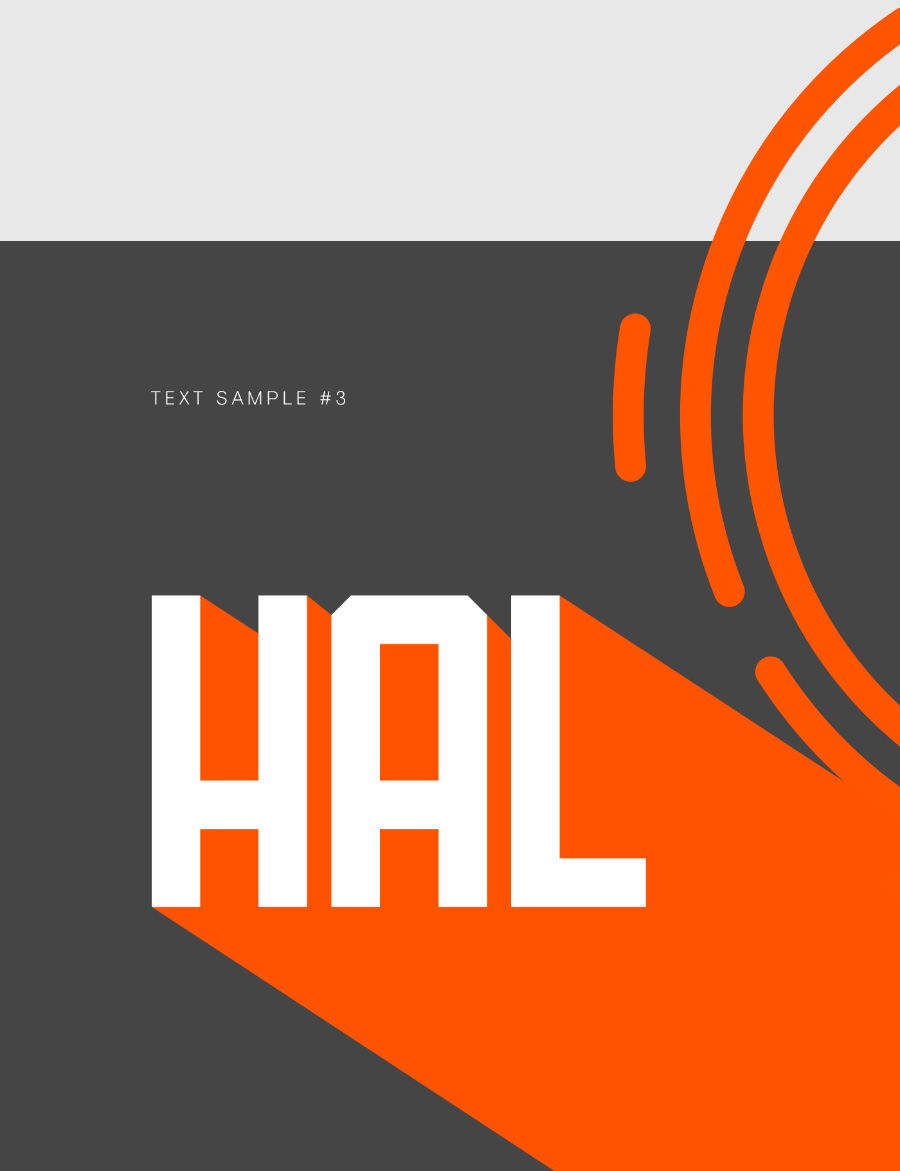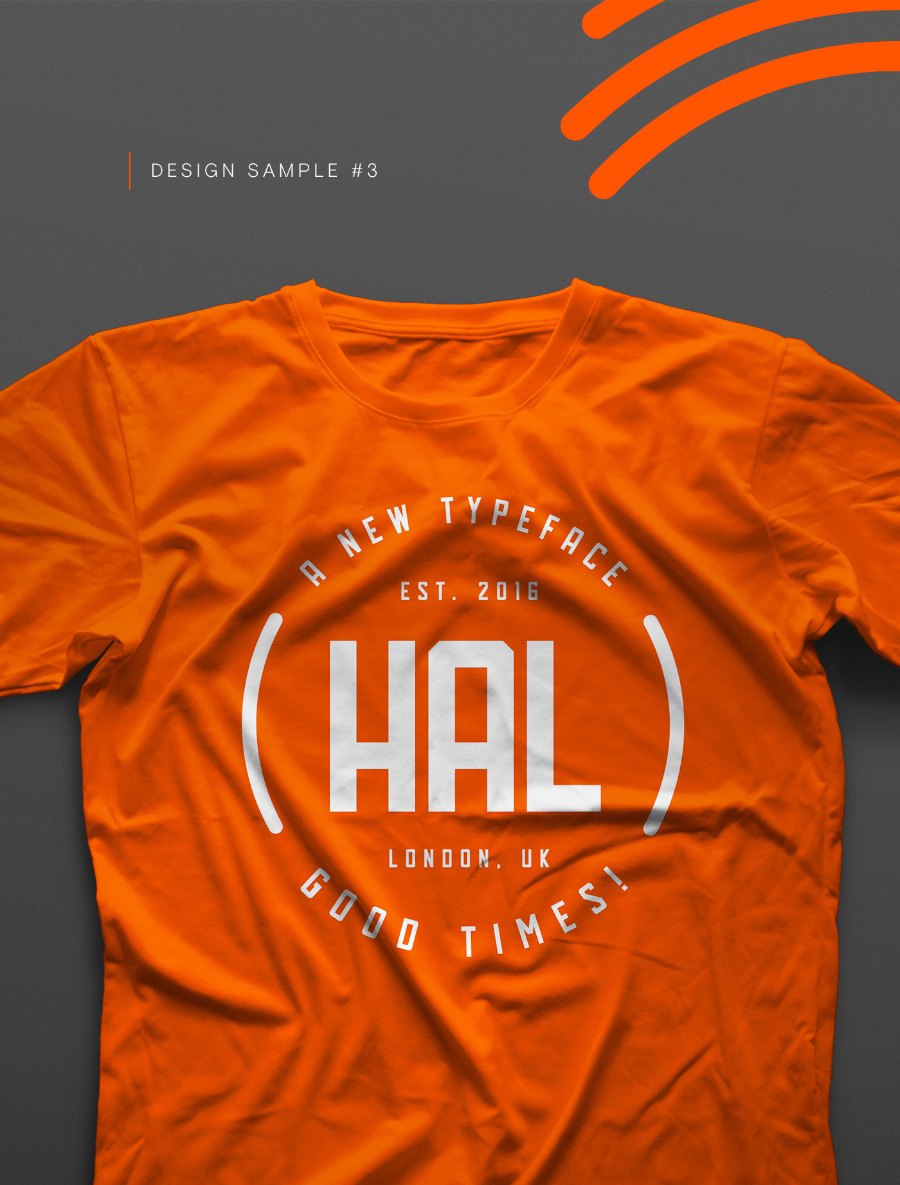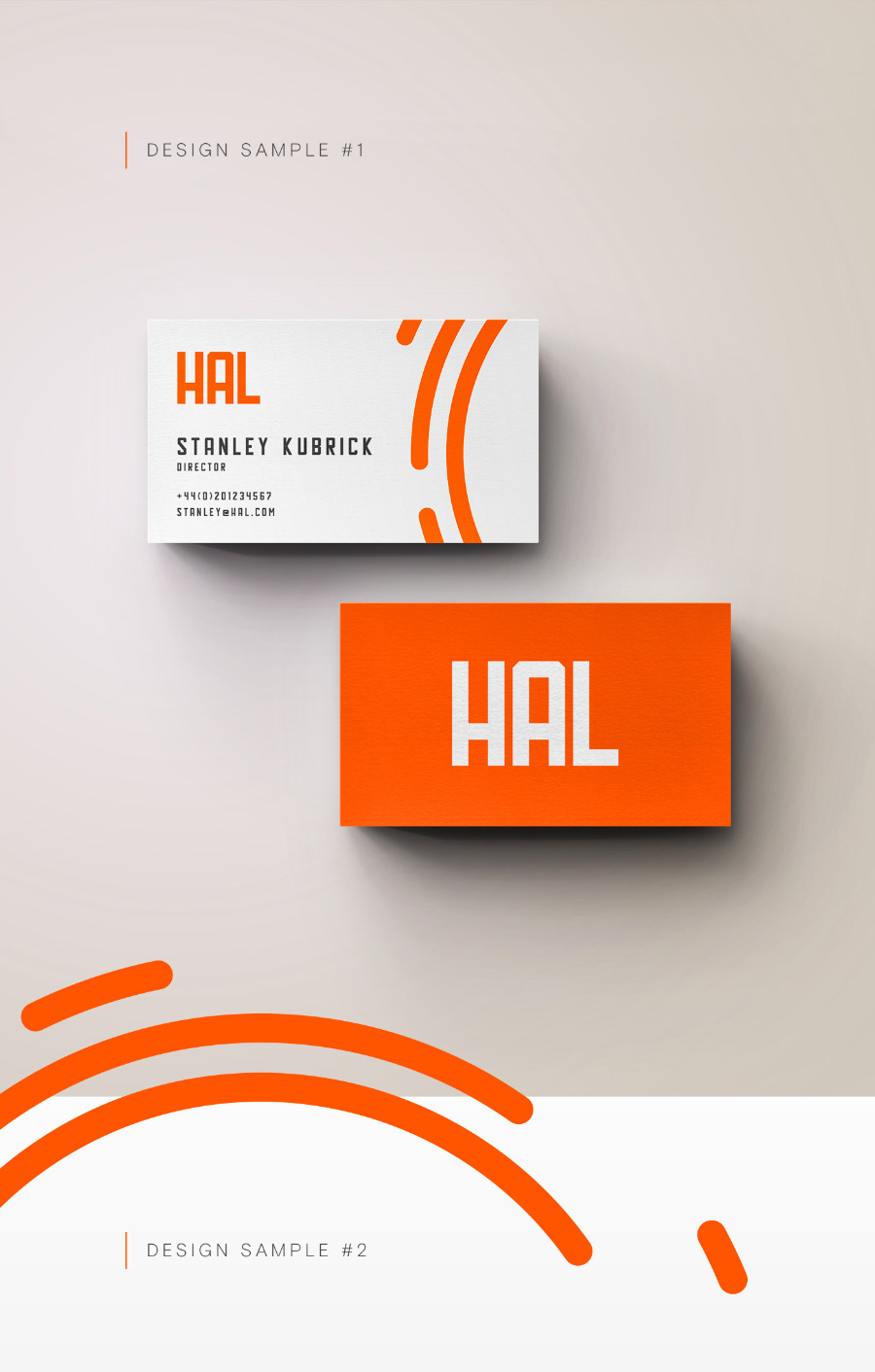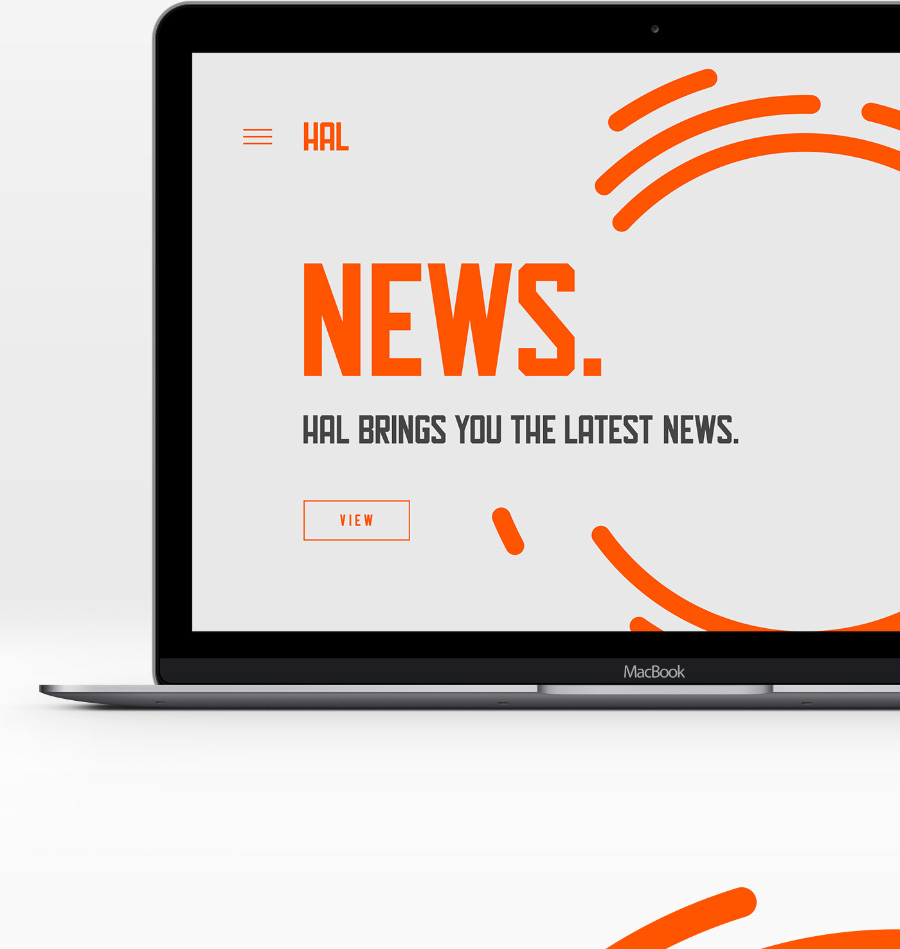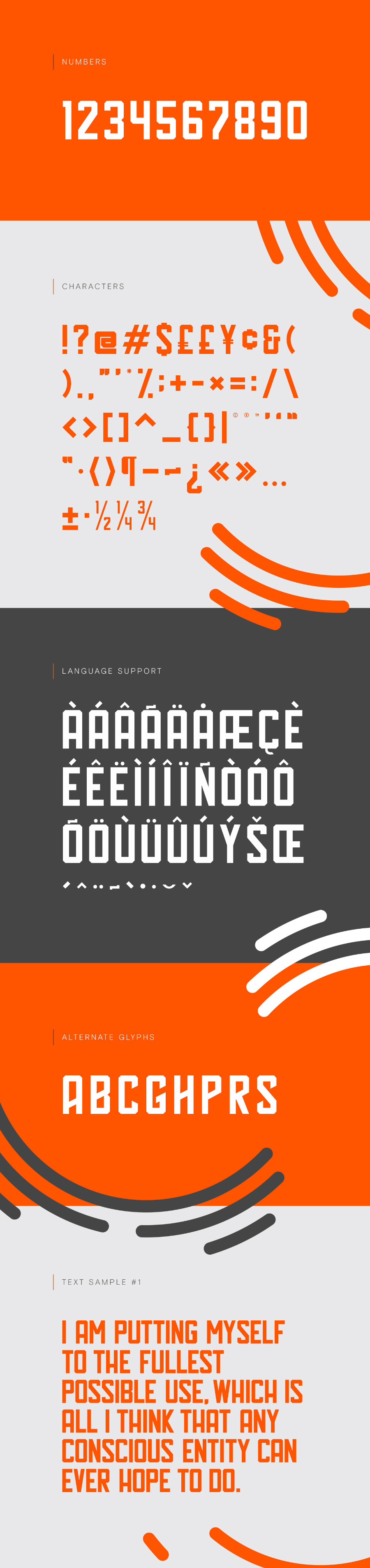
哈尔免费标题字体
Hal Free Headline Typeface
哈尔免费标题字体是一种工业,功利,浓缩设计风格的无衬线字体。这种字体目前只有一个重量。而且,Hal包括扩展语言支持,替代字形,箭头,连字等。 Hal是一种非常灵活的字体,可用于打印和在线使用。哈尔仅供个人使用。对于商业许可的细节,请在这里给我发消息。